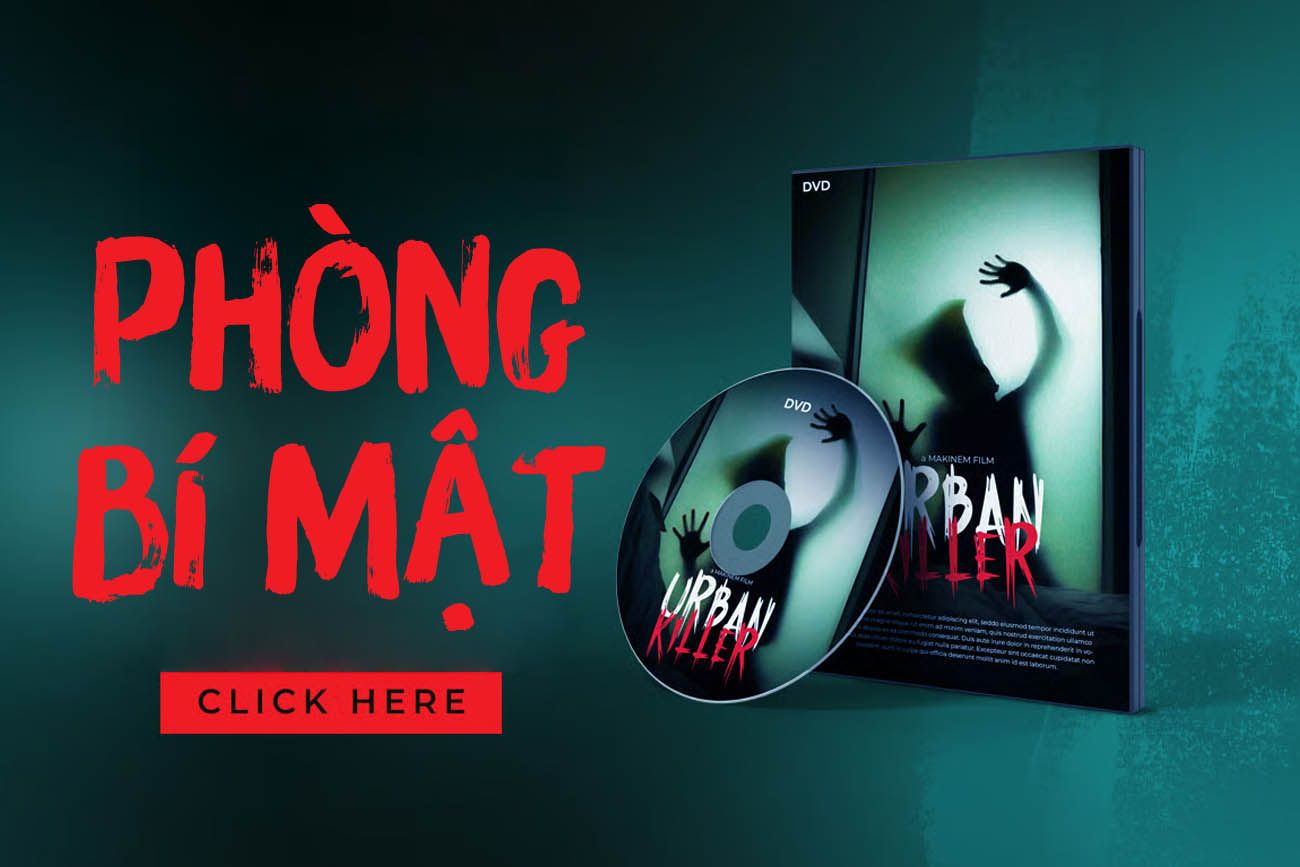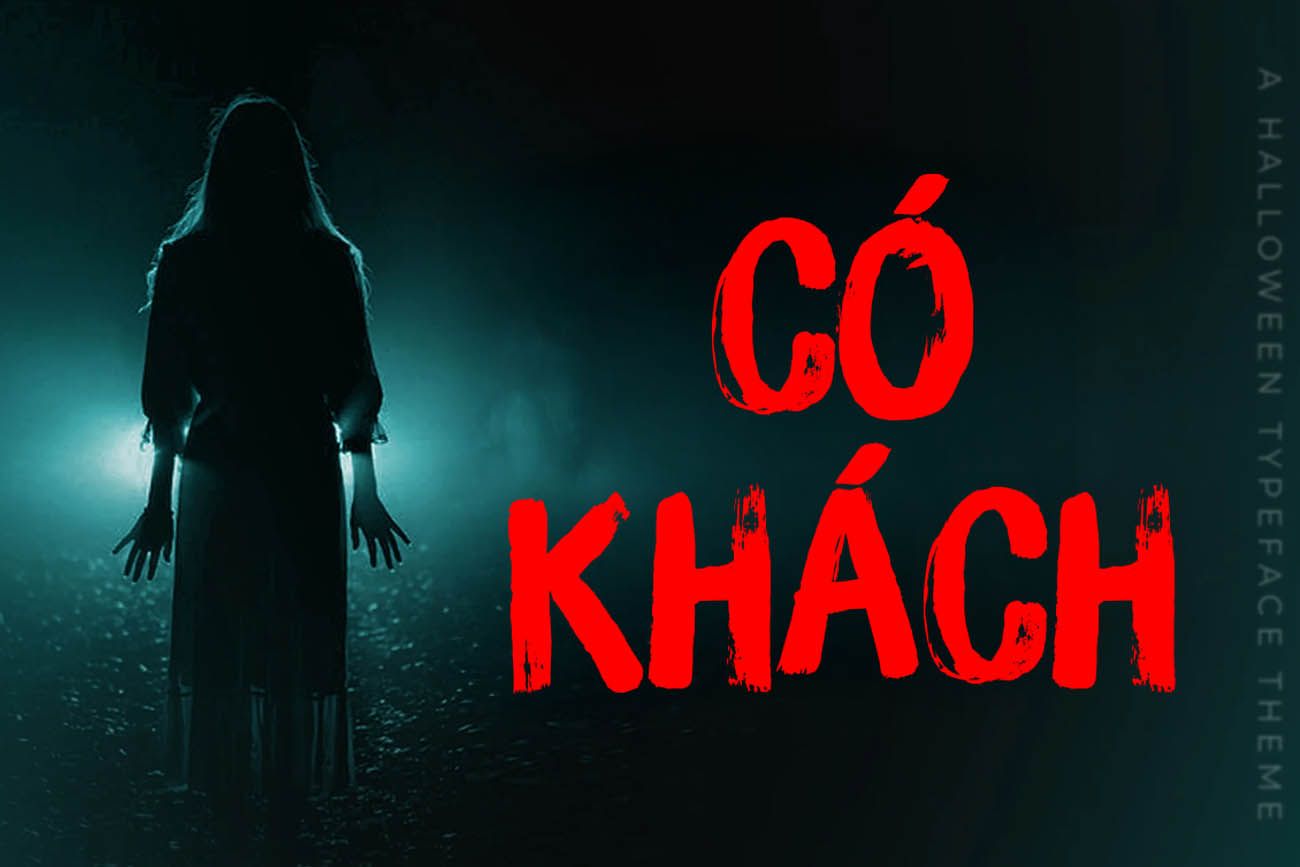
Trong thế giới thiết kế sáng tạo, việc lựa chọn đúng kiểu chữ đóng vai trò cực kỳ quan trọng. Một trong những lựa chọn nổi bật được nhiều designer ưa chuộng hiện nay chính là font iCiel Brush Up – bộ font chữ nét cọ mạnh mẽ, đầy cảm xúc và giàu tính nghệ thuật.
Font Brush Up được thiết kế bởi Marcelo Reis Melo, mang đậm phong cách viết tay bằng cọ với những đường mực thô ráp, phóng khoáng. Phiên bản iCiel Brush Up Việt hóa do iCiel Team thực hiện, hỗ trợ đầy đủ dấu tiếng Việt, giúp các nhà thiết kế dễ dàng ứng dụng vào nhiều dự án trong nước.
Điểm mạnh của font iCiel Brush Up nằm ở hiệu ứng vẽ tay sống động, từng nét chữ loang mực như được tạo trực tiếp bằng cọ thật. Các ký tự in hoa toàn bộ, đường nét dày dặn, khỏe khoắn và tự do, mang lại sự kịch tính và mạnh mẽ cho thiết kế. Đây chính là lý do font thường được xếp vào nhóm font chữ nét cọ ấn tượng nhất hiện nay.
Với phong cách cá tính, font chữ nét cọ này thường được ứng dụng trong:
Poster phim kinh dị, hành động, trinh thám.
Banner sự kiện, game, âm nhạc hoặc cover album.
Thiết kế graffiti, street art, slogan cá tính.
Tiêu đề tạp chí, sách ảnh và các dự án nghệ thuật thị giác.
Nếu bạn đang tìm kiếm một font chữ nét cọ vừa mạnh mẽ vừa khác biệt, thì font iCiel Brush Up chính là lựa chọn hoàn hảo. Bộ font không chỉ giúp thiết kế trở nên nổi bật mà còn truyền tải được cảm xúc mạnh mẽ đến người xem. Với phiên bản Việt hóa hoàn chỉnh, đây là công cụ đắc lực để bạn tạo nên những thiết kế ấn tượng và giàu tính nghệ thuật.